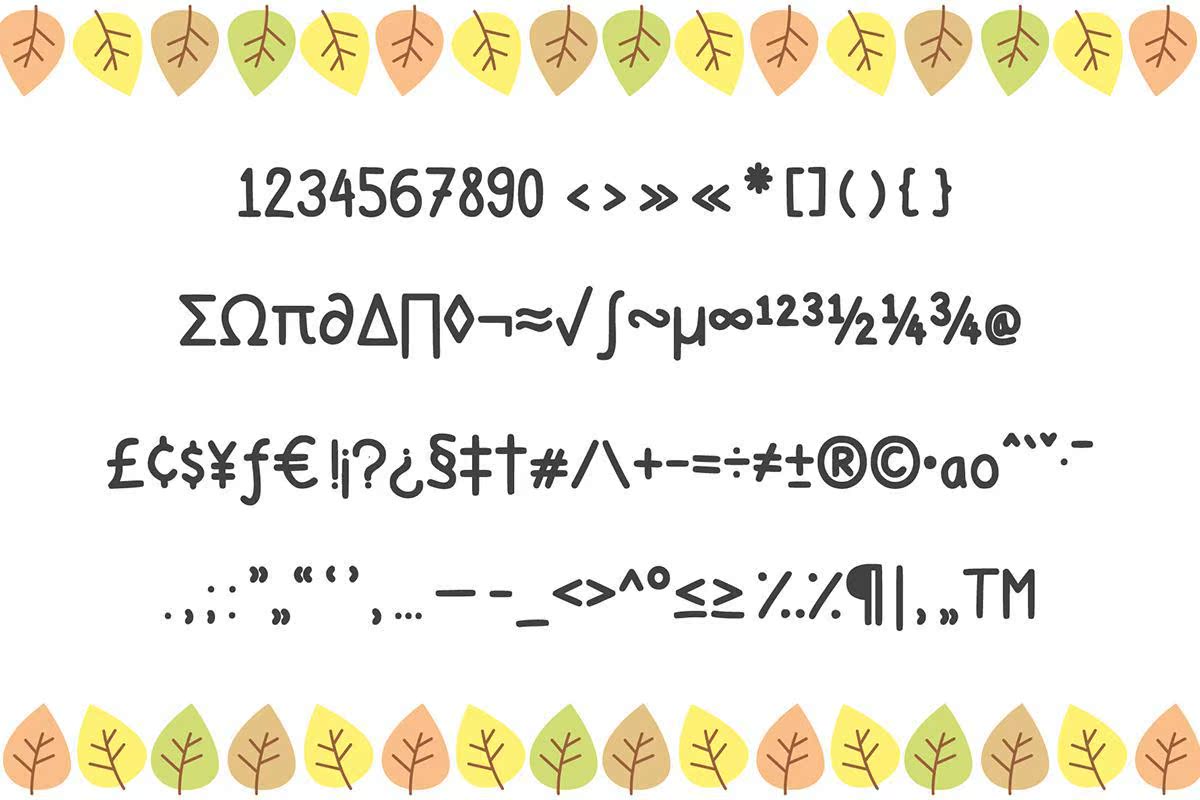
FreeGomGomHandwittenFont是一种可玩的字体。它适用于儿童书籍、包装、礼品卡、横幅、标题文本等。此字体可用于两种格式的文件,您可以使用和安装您的设备。它保存美观的字体,使读卡者了解字体的特征。但是,此FreeFont是个人使用许可证的标志,但是如果你想使用非商业项目,一定要购买。